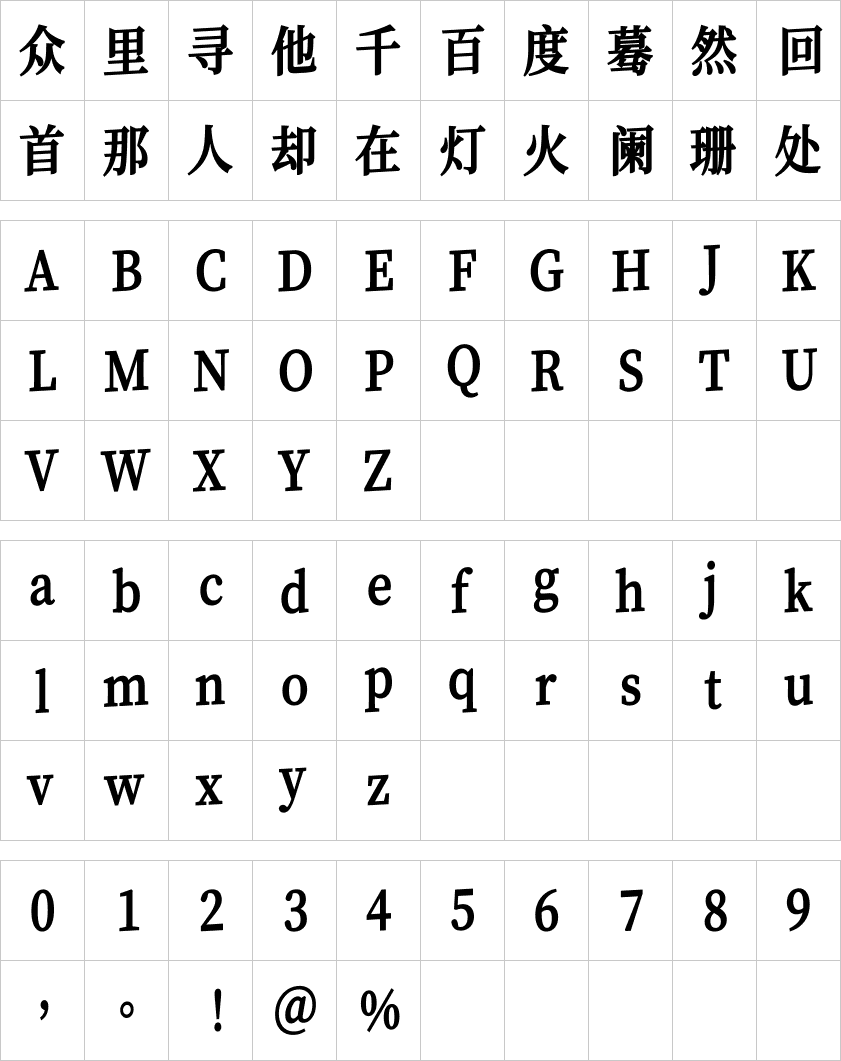
猫啃网文明宋
猫啃网文明宋是猫啃网臻雅宋的升级版本,是猫啃网友@新愚公基于新愚公和谐宋改造的一套免费商用宋体字形。虽“思源屏显臻宋”的原作者定时在修复与更新屏显臻宋,但字体毛刺现象依然存在,作为屏幕显示或日常普通打印问题还不大,若用于海报与喷绘写真上则不太合适。“思源屏显臻宋”的创意是经典的,所以咱东施效颦也做了一个,并增加了5个字重。
猫啃网臻雅宋的长宽比有点怪,似乎不太顺眼,于是“猫啃网文明宋”(L、R、M、S、B、H)略微增加了少许宽度,视觉感要协调一些。